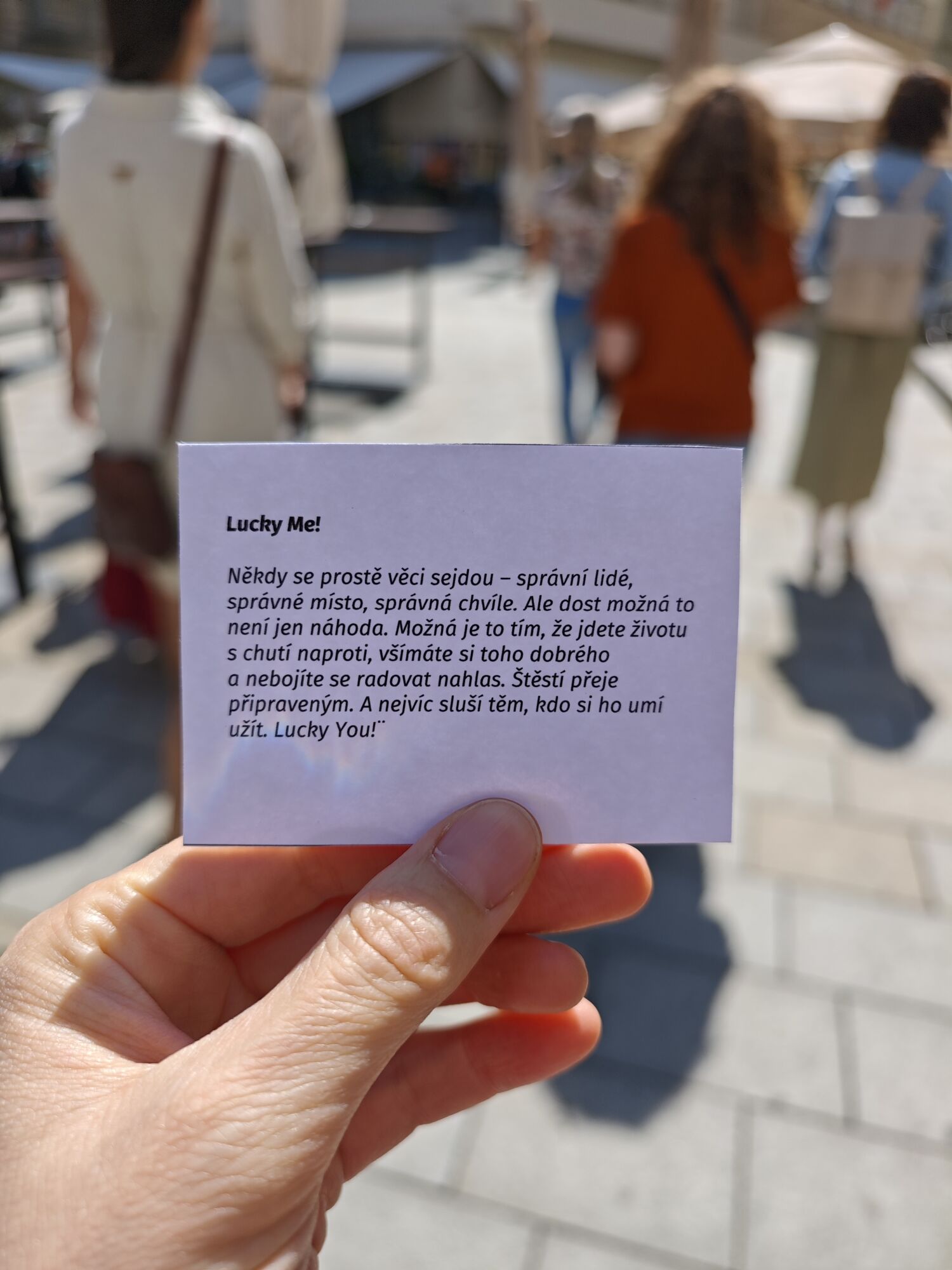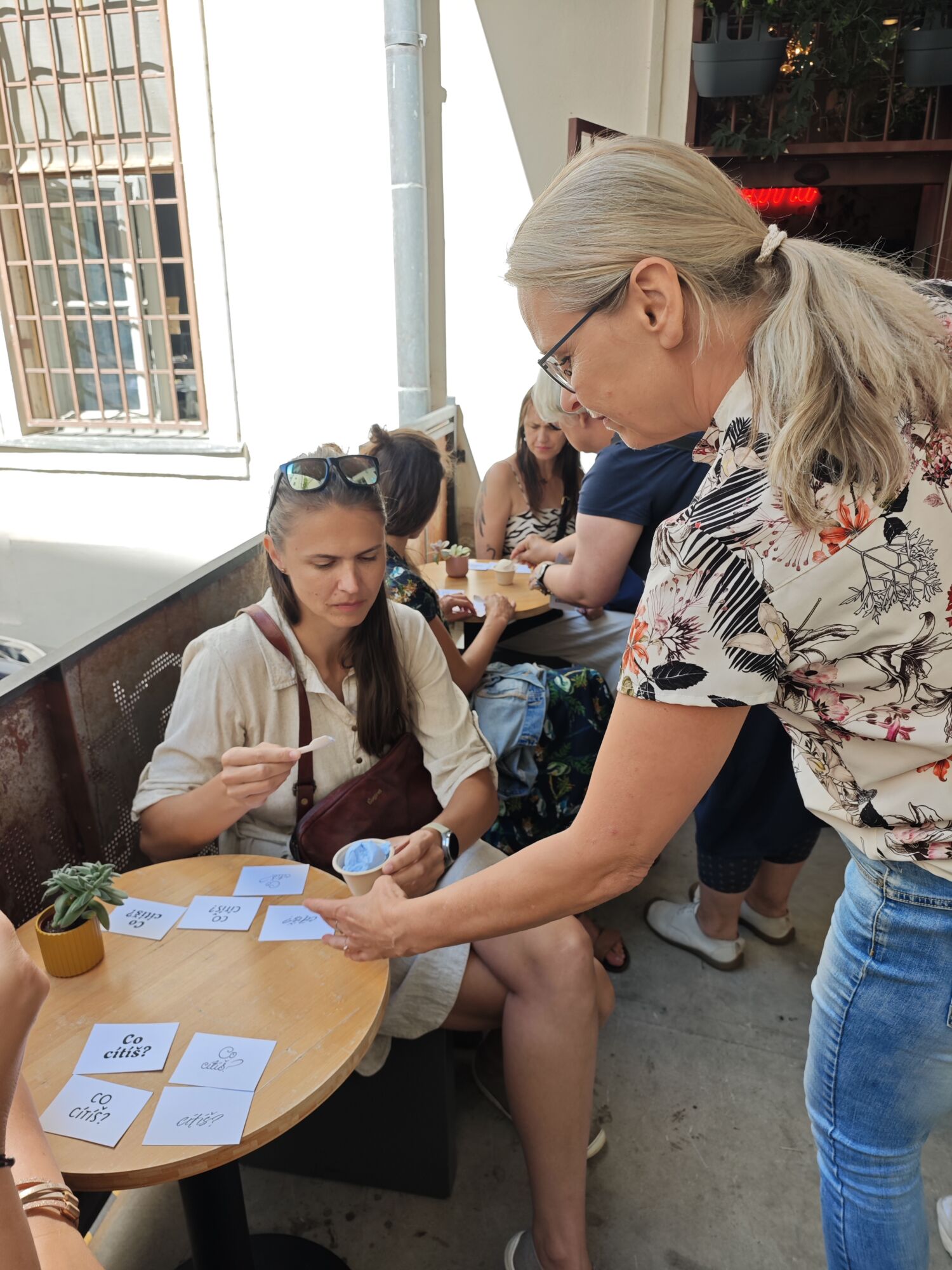
FONTOPROCHÁZKA
Zážitek, který vám změní pohled na svět.
Písmo není detail. Uvidíte, jak ovlivňuje vaše emoce,
podvědomí i značky kolem vás.
Když jsem psala knihu o psychologii fontů, celou dobu jsem se těšila, až převedu vše, co v ní je napsané, do offline živých setkání, která budou úplně novým zážitkem. Chtěla jsem, abyste prožili na vlastní kůži, jak může být FONT průvodcem po cizích zemích i po historii. Jak bez váhání poznáte, které písmo má v sobě zemitost cedru, a které rozevlátost mořského vánku. Jak se stačí dotknout kamene a víte, který font má v sobě jeho strukturu. Jak může font fungovat jako terapeut pro naše nitro. Jak může probudit naše asociace i smysly.
Kniha je dopsaná, tak je čas na setkání v ulicích!
CO VÁS ČEKÁ?
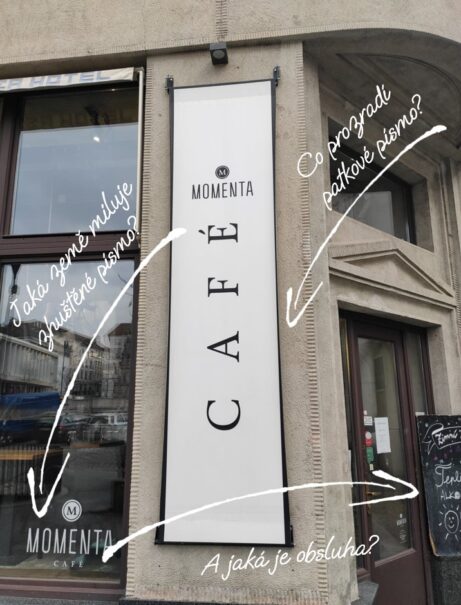
1. ULICE JAKO GALERIE
Procházka Brnem, budeme sledovat vývěsní štíty, nápisy na zdech i výlohách obchodů. Dotkneme se marketingu i historie, pikantních historek o písmu i psychologie fontů.
2. FONTY VŠEMI SMYSLY
Na tajných místech v Brně si fonty ochutnáme, poslechneme, osaháme. Prožijete na vlastní kůži, že každý font má svou chuť, vůni, zvuk... Připravím pro vás testovací sady, kartičky, které si odnesete i s poznámkami.
3. TO JSEM JÁ, PŘES FONTY
Malé sebepoznávací zastavení. Podíváte se do zrcadla, které vám fonty nastaví. Co všechno vám o vás mohou prozradit?
To vše zažijete v průběhu 3 hodin při procházce, která povede centrem Brna a jeho zajímavými zákoutími. V malé skupince se můžete nechat nakazit vášní pro písmenka, která každý den ovlivňují naše rozhodování. A vy už budete vědět jak a proč.
Fontoprocházky jsou o objevování příběhů. Příběhů skrytých za písmem na fasádě, na vývěsním štítu, na parfému, ke kterému přivoníte.
Příběhů, ve kterých je písmo cítit po vanilce nebo po citrónu. Příběhů, ve kterých je drsné jako kámen v hradbách na Špilberku i jemné jako hedvábný šátek ve výloze.